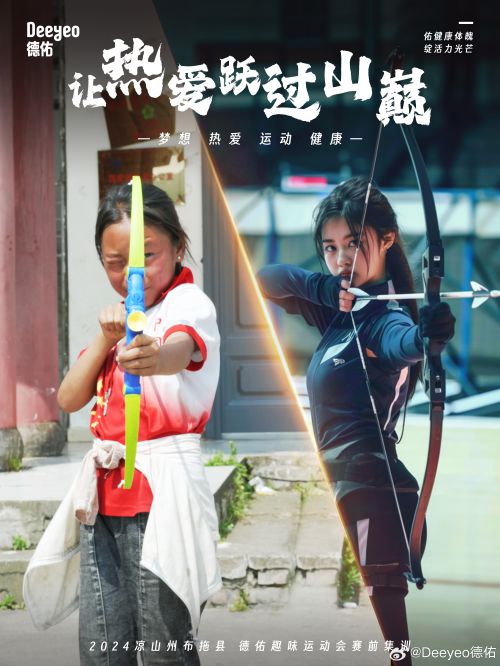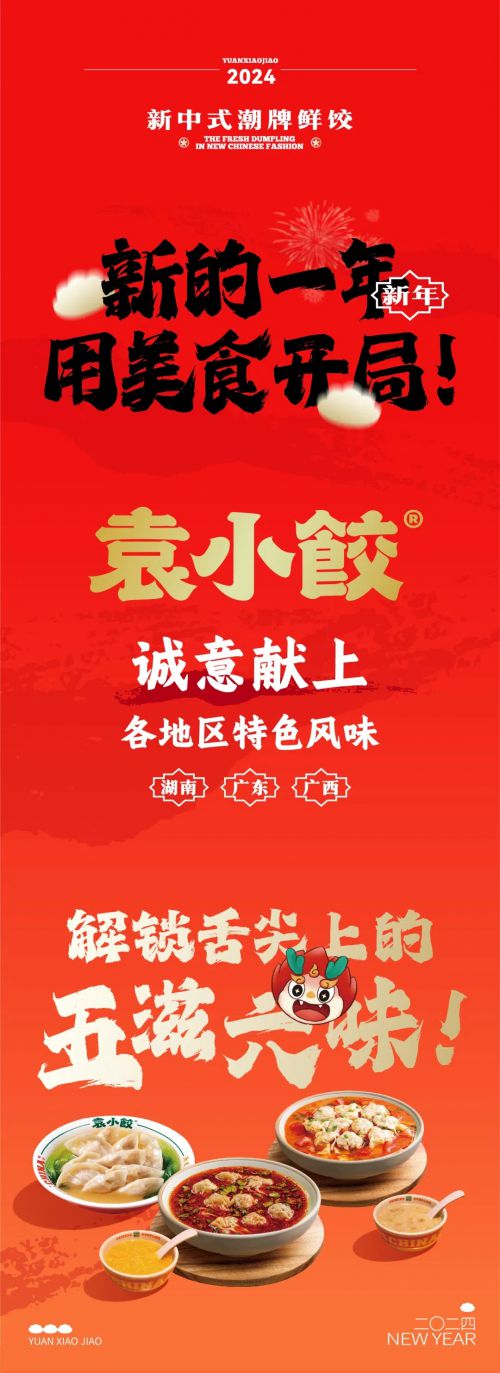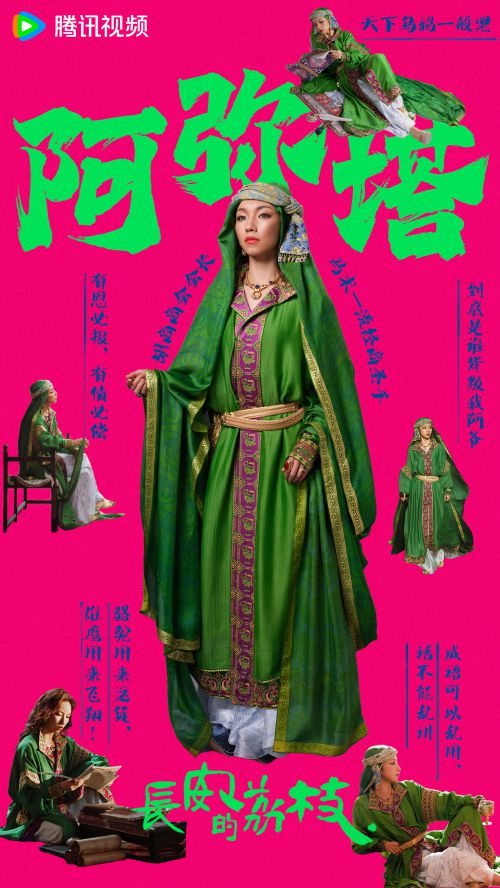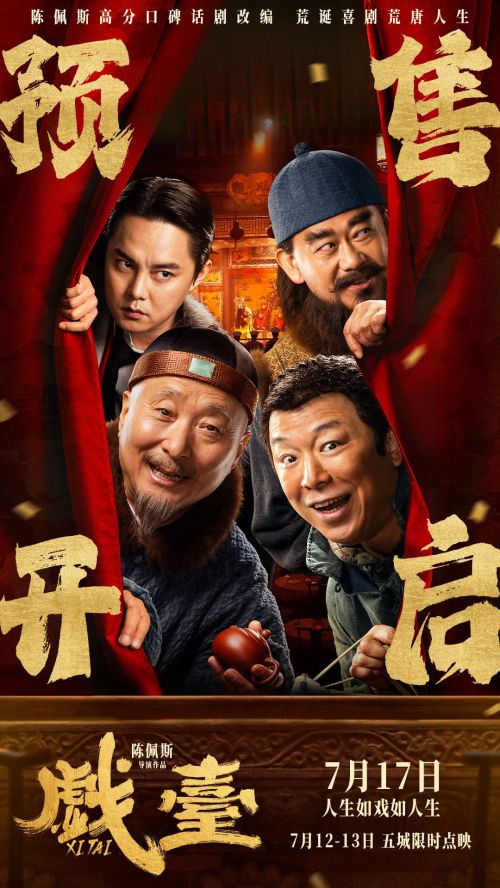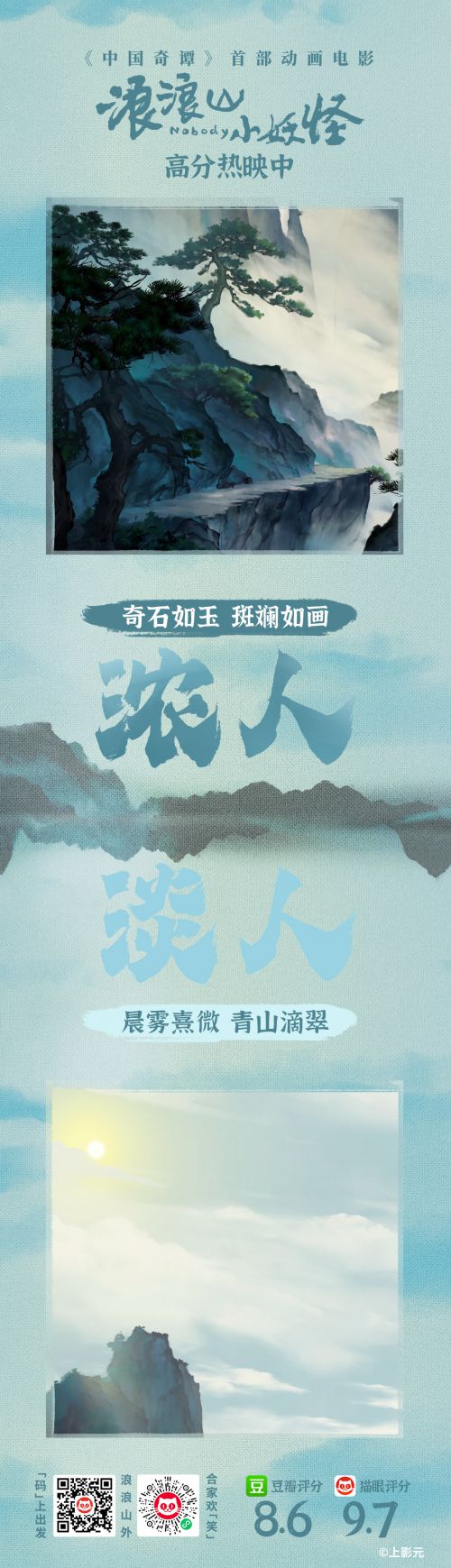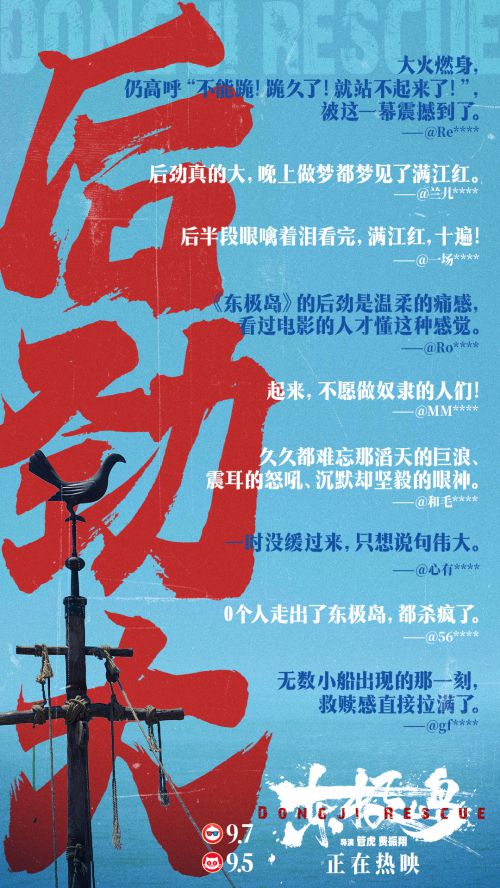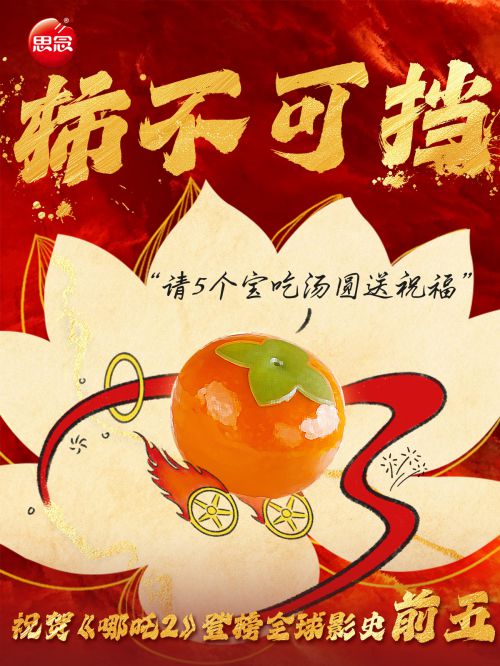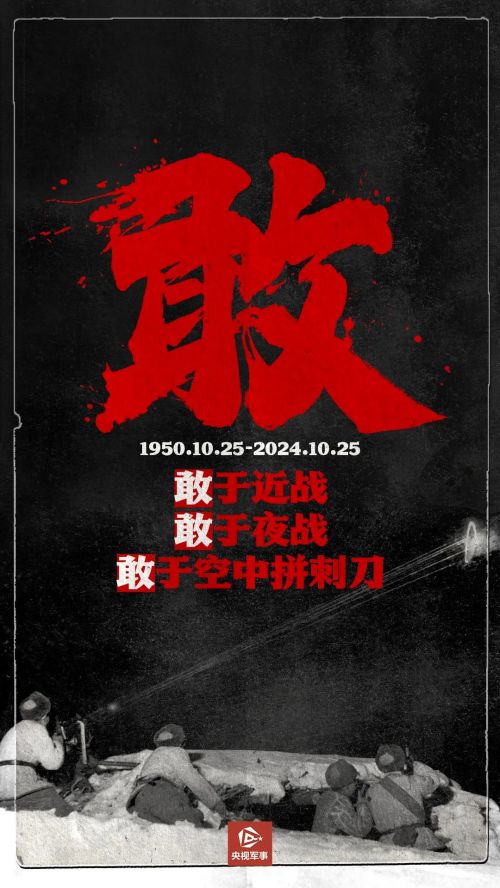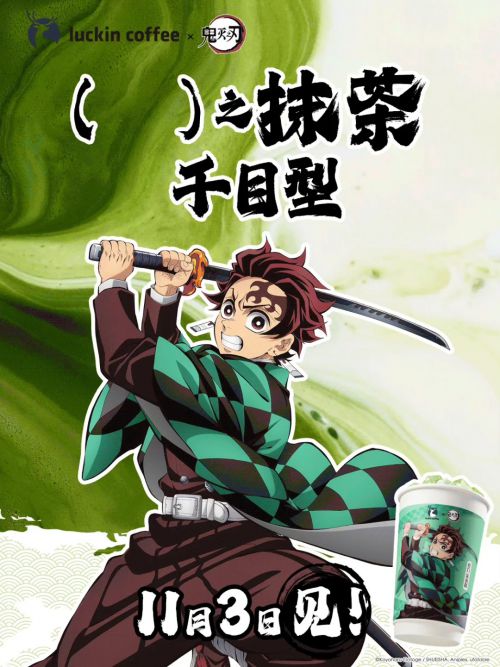
点字狂澜
【点字狂澜】是点字库推出的超粗手写体字体,以中国风笔触与豪放气势著称,兼具力量感与艺术张力,支持简体/繁体中文常规字符集,适合会员商用授权场景。 点字狂澜字形修长挺拔,重心设计偏高,配合宽博中宫结构,展现出开阔雄劲的视觉效果。笔型融入斜切设计,方头笔画与断开式连接形成独特节奏,起笔转折处棱角分明,既保留手写体的随性洒脱,又通过均匀加粗的线条强化了字体的厚重质感。 点字狂澜将传统书法的笔墨韵味与现代设计需求巧妙融合,用笔大胆豪放,线条复叠处尽显浑厚笔力,既有雍容大度的沉稳气质,又暗藏蓄势待发的动态张力。无论是标题设计、文化宣传还是品牌标识,均能以鲜明的视觉冲击力传递中式美学精神,是兼具艺术性与实用性的手写字体选择。